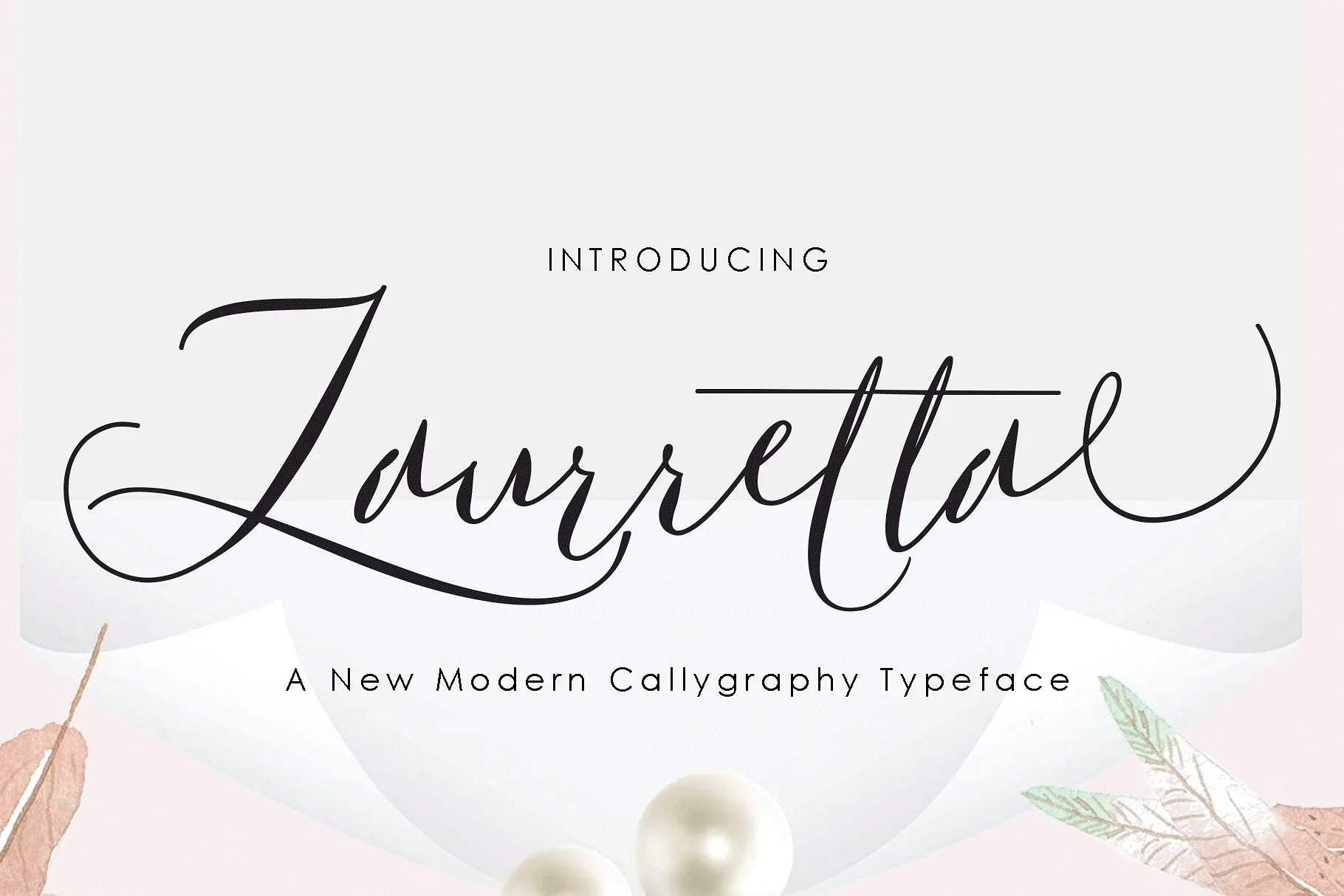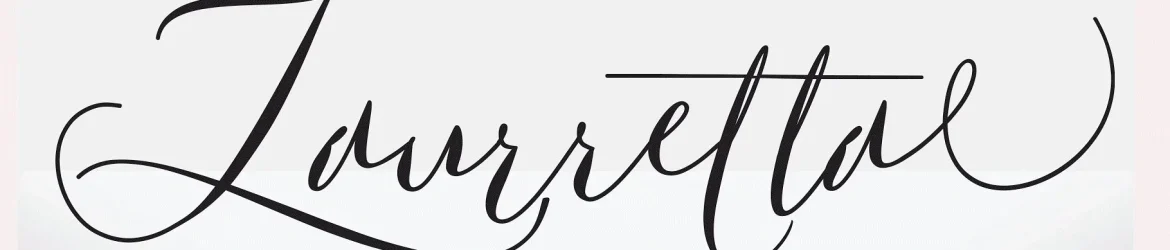
Laurretta Calligraphy Font – Download Grátis
Laurretta Calligraphy Font é uma elegante tipografia moderna que transmite conforto ao usuário graças à sua textura suave e nuances refinadas. Introduzimos Laurretta Calligraphy, uma fonte concebida a partir de traços manuscritos, destacando-se por seus formas contemporâneas e únicas na escrita calligráfica. A escrita tem um estilo extremamente natural e perfeita para aplicação em variados projetos. Este é o ideal para logotipos, camisetas personalizadas, embalagens de produtos, cabeçalhos, cartazes, cartas de cumprimentos e muito mais. Laurretta Calligraphy é uma escolha ideal se você está buscando uma fonte moderna e elegante para seus projetos visuais.